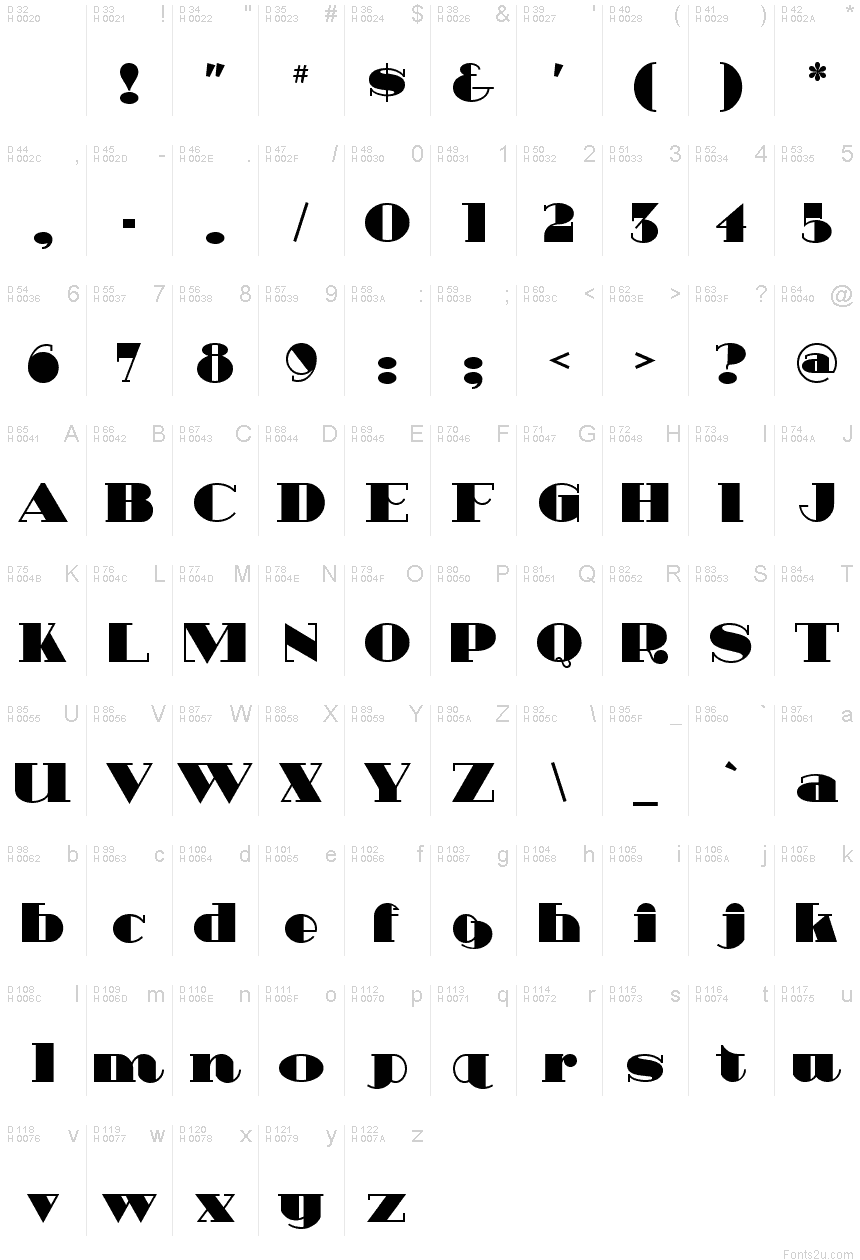
HeavyTripp UltraBold 字体
HeavyTripp UltraBold
由 Nick Curtis 设计的 HeavyTripp Ultra Bold 是一款免费的复古展示字体,其视觉冲击力犹如 60 年代摇滚演出现场的黑墨印刷海报。粗壮的方块字形被清脆的圆形镂空和锐利的楔形切口分割,赋予每个单词强劲、类似模版刻字(stencil)的律动感。HeavyTripp 系列中的 UltraBold 样式,即便是最短的标题,也能呈现出跃然纸上的立体感。
HeavyTripp Ultra Bold 的设计初衷就是为了大字号排版——让它在演出海报、专辑封面、杂志、饮料标签、复古品牌设计以及醒目的社交媒体图文中尽情张扬。它那厚实的字形在远处依然清晰易读,近看则充满别致与时尚感。这款免费字体最适合搭配简洁、纤细的无衬线字体作为正文使用,让 HeavyTripp Ultra Bold 成为无可争议的焦点。